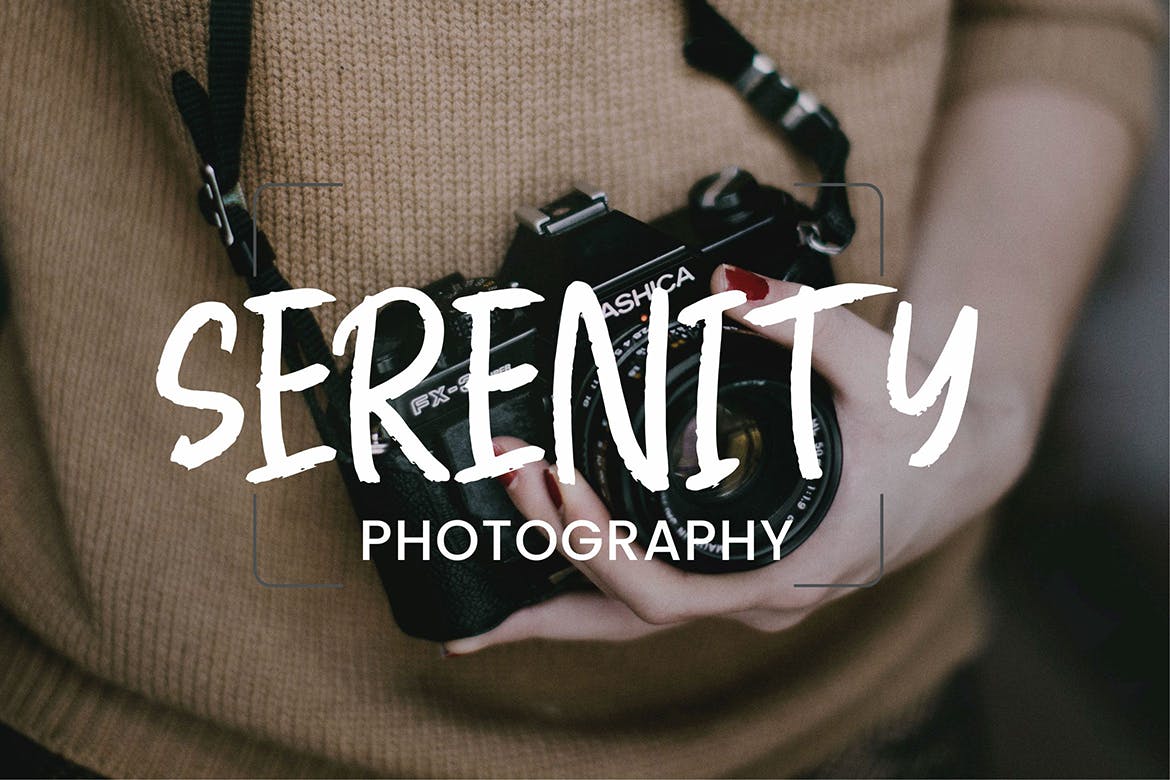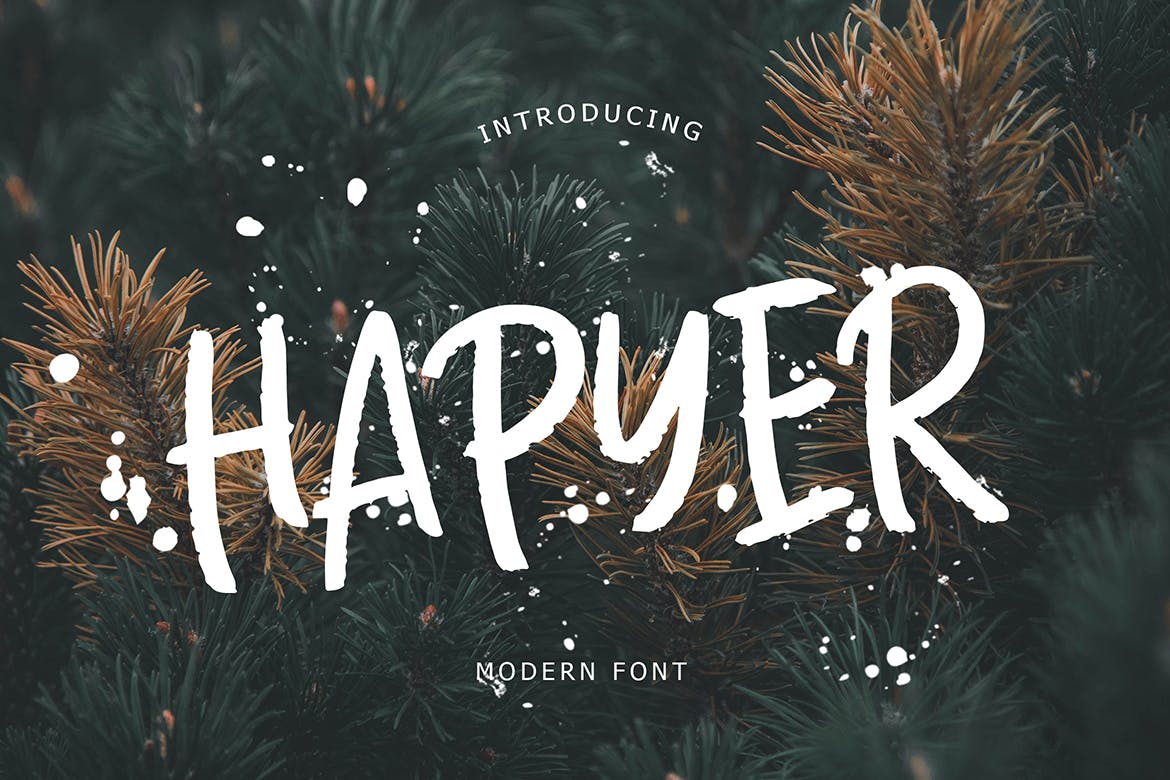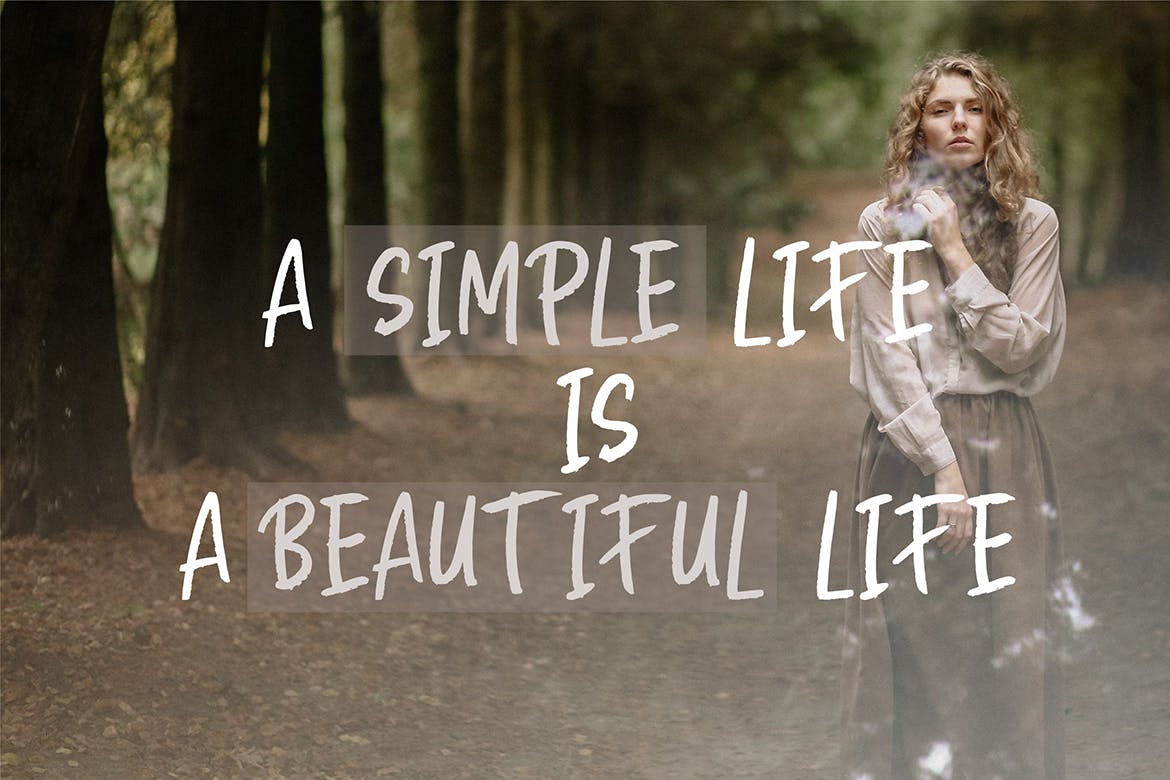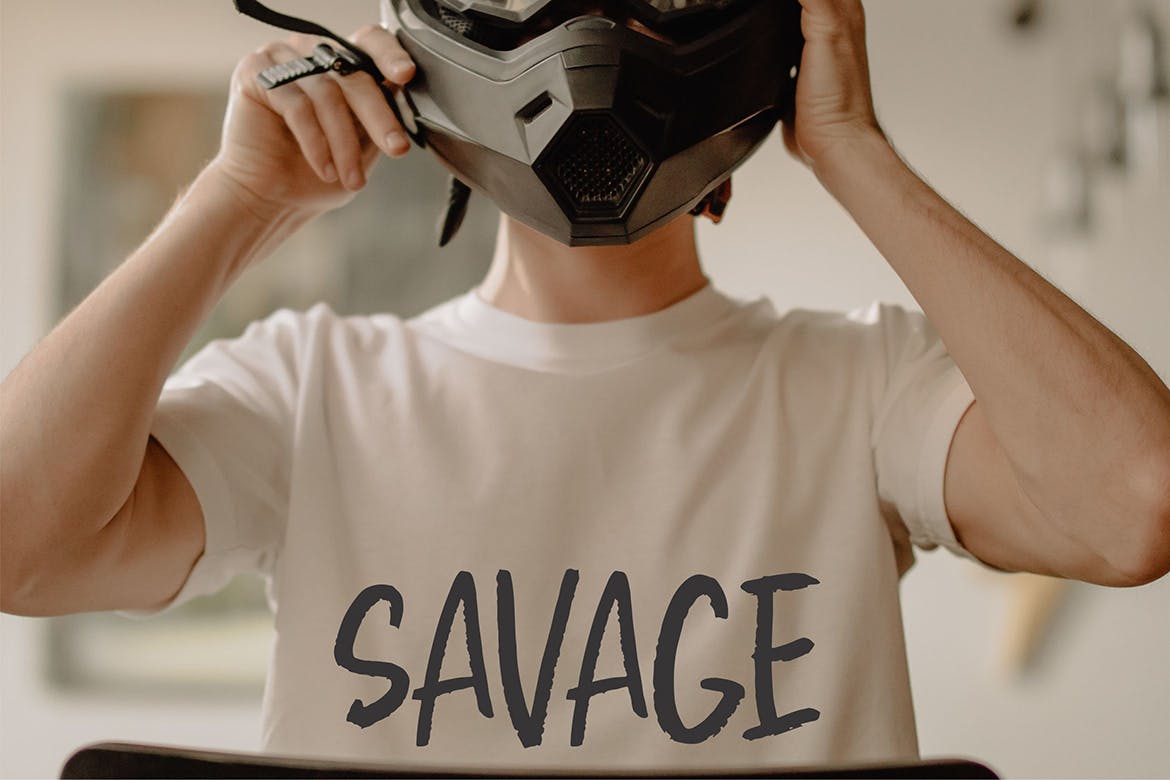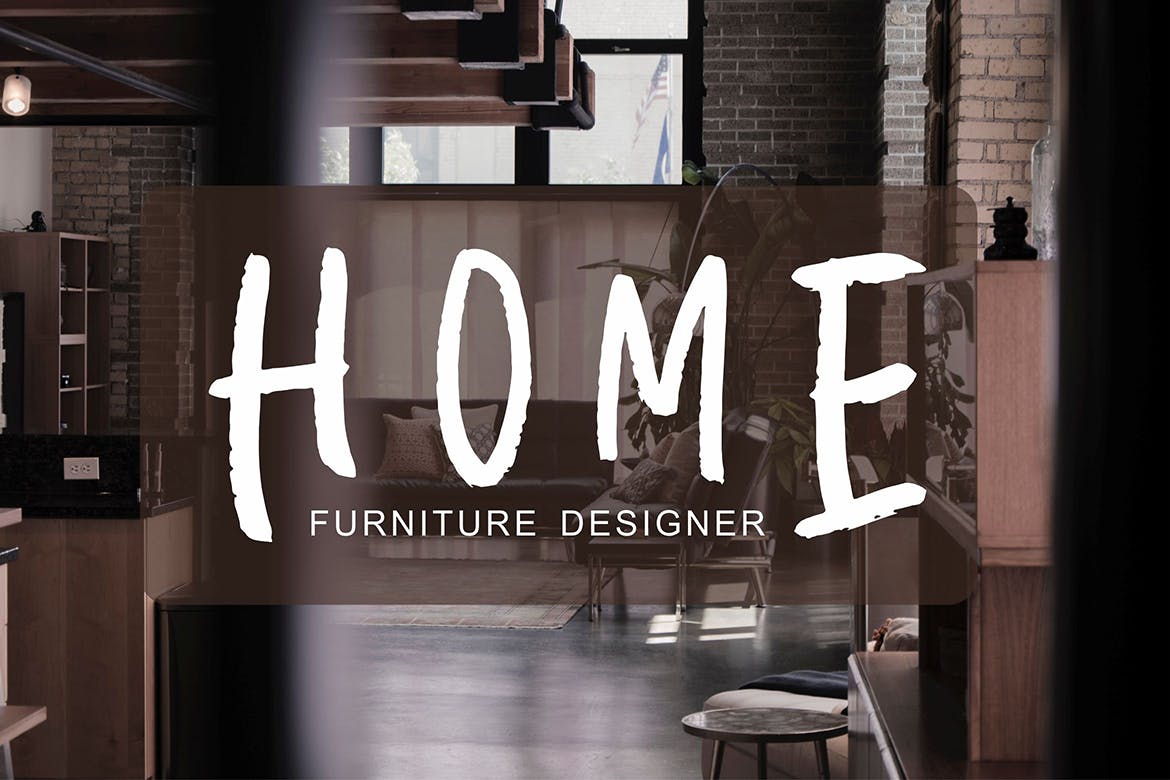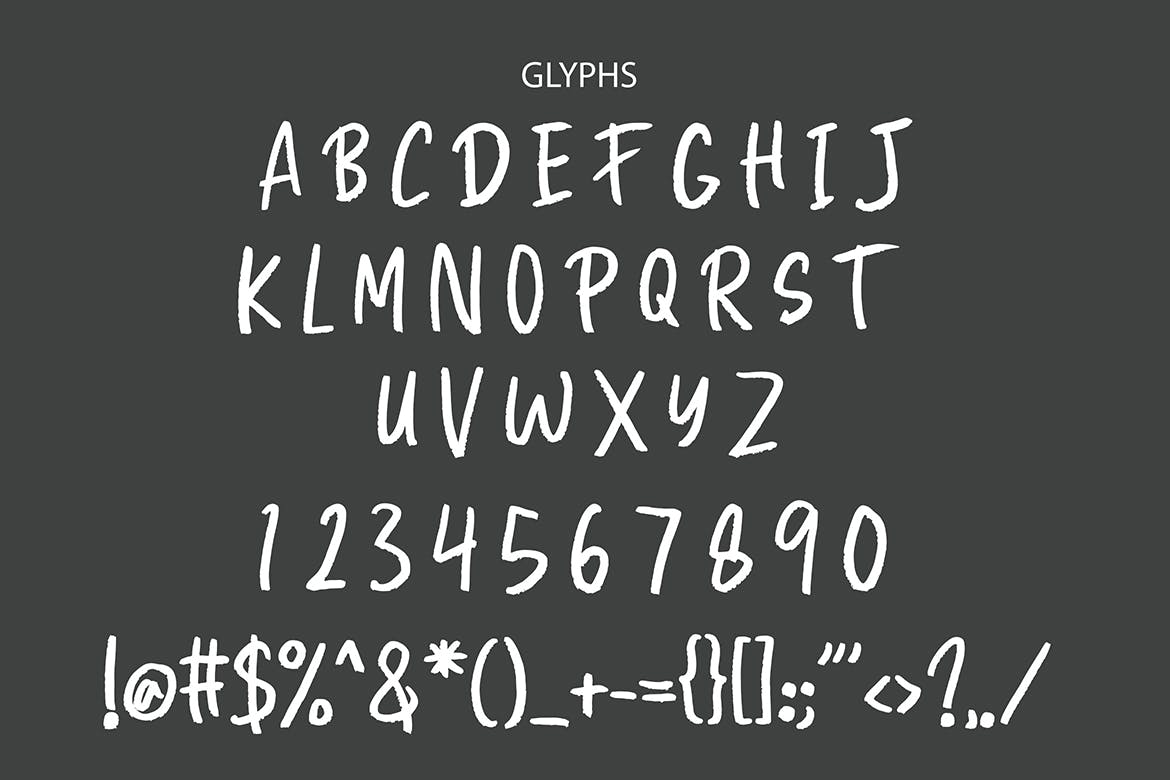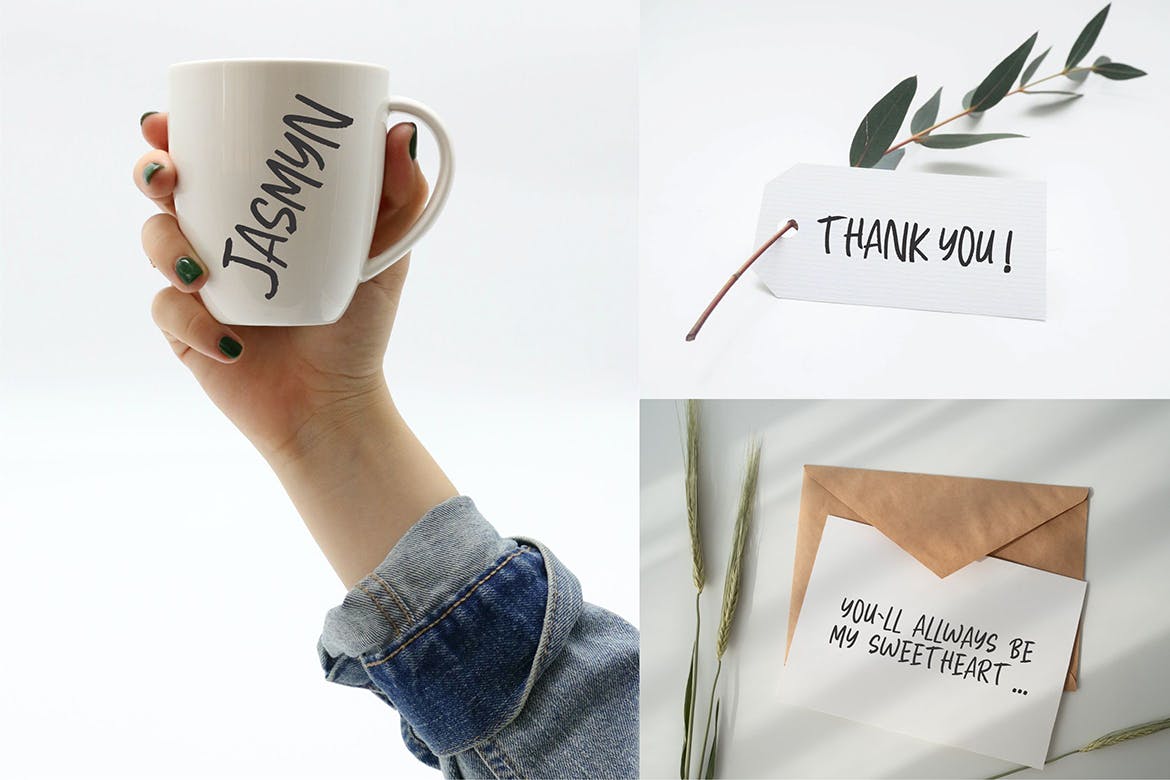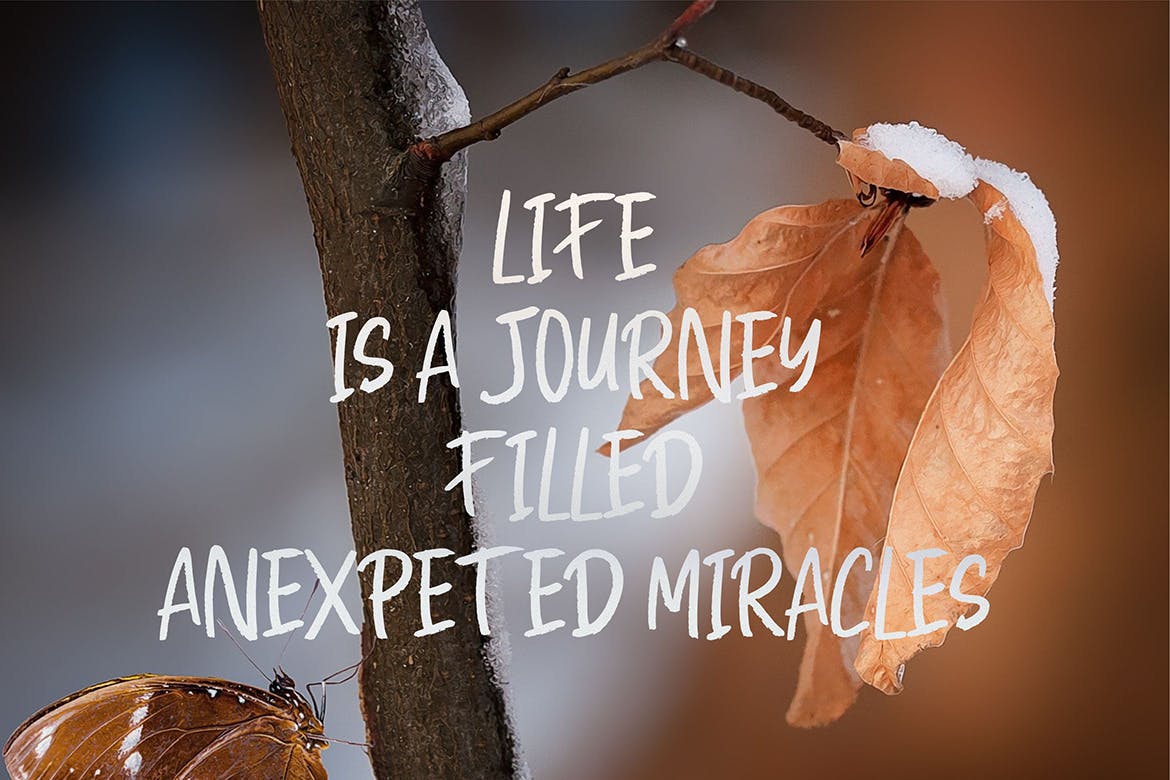
دانلود فونت مدرن Hapyer برای طراحی‌های خلاقانه
Hapyer Modern Font
فونت دست‌نویس مدرن Hapyer، انتخابی ایده‌آل برای پروژه‌های طراحی شما.
Hapyer یک فونت دست‌نویس مدرن است که برای پروژه‌های برندسازی، طراحی لوگو، تی‌شرت، پست‌های شبکه‌های اجتماعی، تبلیغات، بسته‌بندی محصولات، طراحی محصولات، برچسب، واترمارک، دعوت‌نامه، لوازم‌التحریر و هر نوع پروژه‌ای مناسب است.